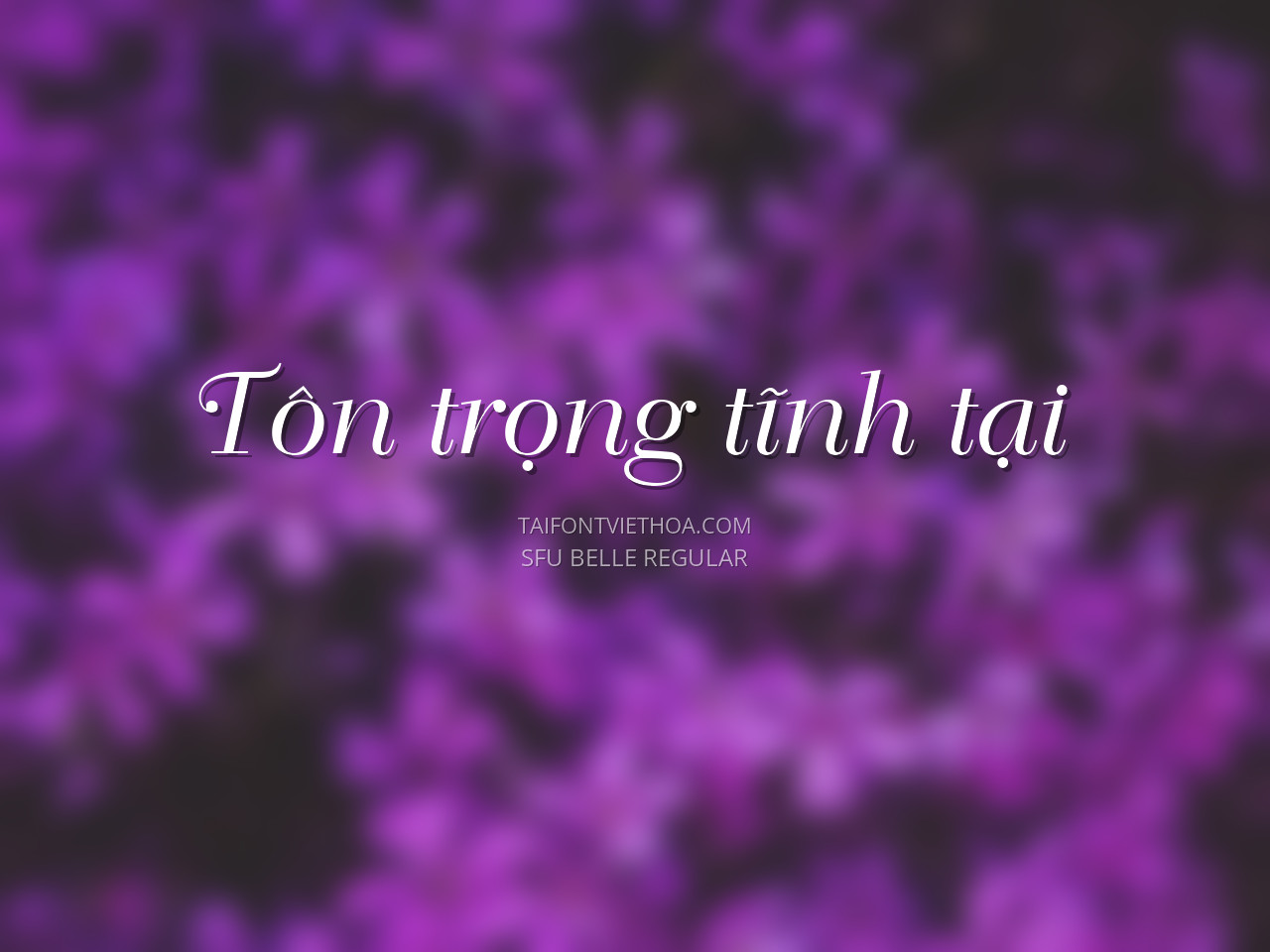
Giới thiệu về font SFU Belle – Thanh lịch, nữ tính và cuốn hút
SFU Belle là phiên bản Việt hóa của font Belle – một kiểu chữ serif hiện đại mang đậm chất thời trang, được lấy cảm hứng từ những thiết kế haute couture và tạp chí cao cấp. Belle không chỉ đơn thuần là một serif cổ điển, mà còn pha trộn nét hiện đại đầy quyến rũ, với phần chân chữ tinh tế và tỷ lệ chữ mang cảm hứng từ thế kỷ 20. Font được phát triển với mục đích tạo nên sự khác biệt cho các thiết kế cao cấp, đặc biệt là trong ngành làm đẹp và thời trang.
Phiên bản SFU Belle được Việt hóa hoàn chỉnh, hỗ trợ đầy đủ dấu tiếng Việt cùng hơn 90 ngôn ngữ khác. Taifontviethoa.comđã chọn lọc và chia sẻ bộ font này nhằm đáp ứng nhu cầu thiết kế sang trọng, thời thượng và mang tính cá nhân hóa cao, phục vụ cho các thương hiệu cao cấp tại Việt Nam trong lĩnh vực mỹ phẩm, thời trang, sự kiện hoặc xuất bản chuyên đề đặc biệt.
Thiết kế thời trang và quý phái – Lựa chọn lý tưởng cho thiết kế cao cấp
SFU Belle sở hữu cấu trúc serif thanh thoát, có độ tương phản vừa phải giữa các nét, các ký tự mang đường cong mềm mại và dáng chữ hơi cao giúp tạo hiệu ứng thị giác kéo dài, uyển chuyển và cuốn hút. Font đặc biệt phát huy hiệu quả khi được sử dụng ở kích thước lớn, trong tiêu đề, bao bì sản phẩm hoặc thương hiệu cần thể hiện sự thanh lịch và tinh tế.
Ứng dụng lý tưởng: logo thương hiệu mỹ phẩm, tiêu đề tạp chí thời trang, thiệp mời sự kiện cao cấp, nhãn hàng trang sức, wedding branding, thiết kế editorial và hệ thống nhận diện thương hiệu sang trọng. Ngành nghề phù hợp: thời trang, làm đẹp, sự kiện cưới hỏi, mỹ phẩm, lifestyle và thiết kế boutique cao cấp.